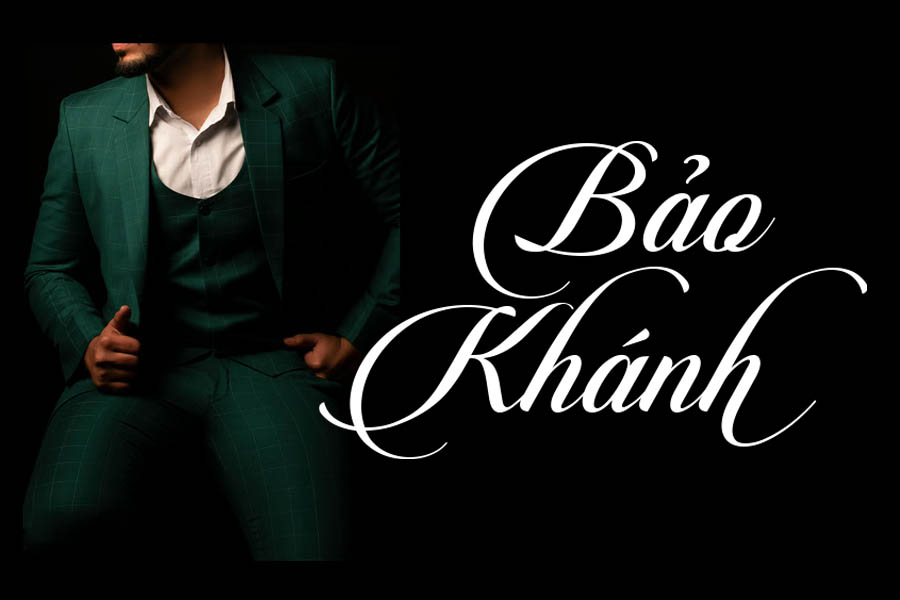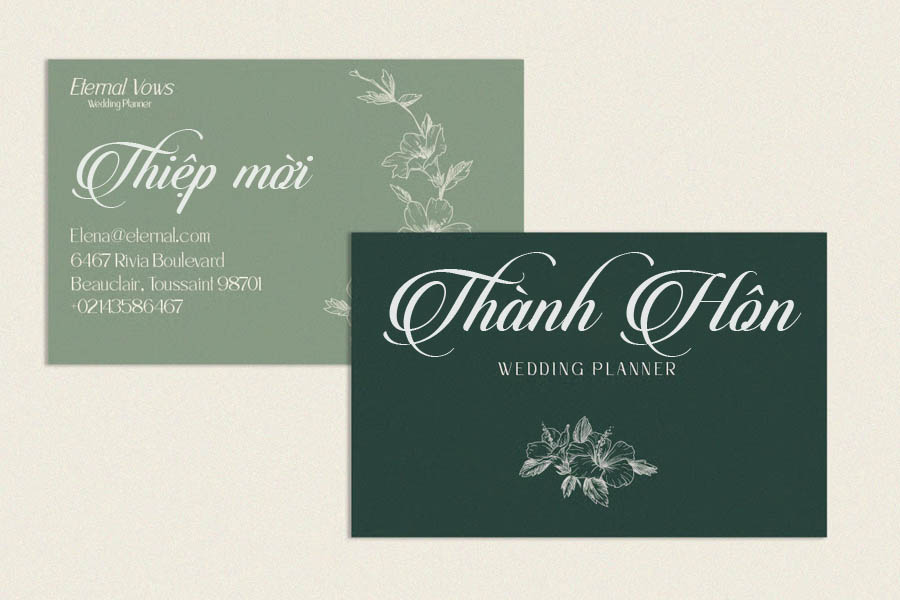
Giới thiệu SVN Candlescript Pro
Font SVN Candlescript Pro là một trong những font chữ viết tay đẹp được ưa chuộng trong thiết kế hiện đại. Với đường nét mềm mại, uốn lượn tự nhiên, SVN Candlescript Pro mang lại cảm giác tinh tế, nhẹ nhàng nhưng vẫn đầy cá tính. Font được thiết kế bởi Måns Grebäck – nhà thiết kế nổi tiếng với các kiểu chữ script đậm chất nghệ thuật.
Đặc biệt, Candlescript Pro đã được Việt hóa đầy đủ, hỗ trợ dấu tiếng Việt rõ ràng, giúp người dùng Việt dễ dàng sử dụng cho các dự án thiết kế như logo, thiệp cưới, bao bì sản phẩm, blog cá nhân hay tiêu đề sách báo mang phong cách lãng mạn, cổ điển.